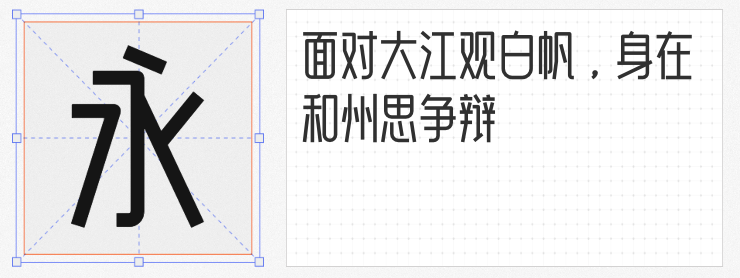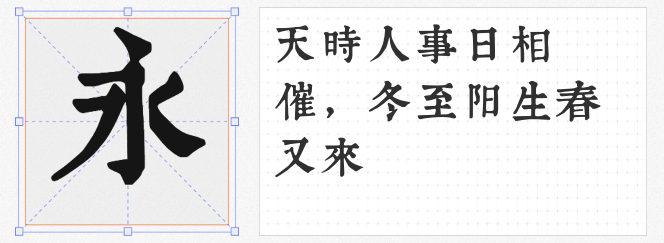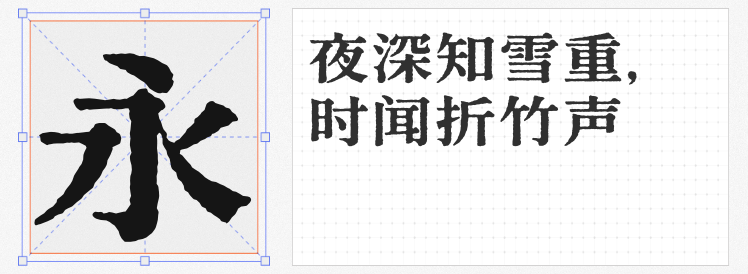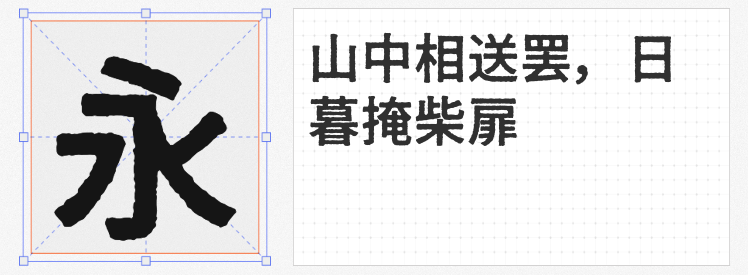
在复古风格的设计中,字体是连接过去与现在的视觉纽带。以下四款免费商用字体,以独特的造型语言与岁月质感,为设计注入跨越时空的叙事感。
1. 白无常可可体 Medium
这款修长挺拔的创意字体,以干净的几何线条重构汉字结构。转角处采用规则的圆形切割,在硬朗的直线中融入圆润的呼吸感,形成理性与感性的微妙平衡。其简洁的笔画与克制的装饰性,既保留了工业时代的机械美学,又通过修长比例暗合复古海报的优雅气质。适用于蒸汽朋克主题、科技品牌怀旧营销等场景,为现代设计注入一丝未来主义的复古情怀。
2. 寒蝉活黑体 復 Bold
基于ShipporiAntique改造的这款黑体,完美复刻了老式印刷品的磨损质感。斑驳的笔画边缘仿佛被岁月侵蚀,粗犷的笔触中透露出手工印刷的温度。作为思源黑体的衍生字体,它在保留现代黑体易读性的同时,通过纹理处理赋予文字历史厚重感。特别适合复古电影海报、旧时光主题包装设计,或需要营造沧桑感的品牌故事呈现。
3. 润植家康熙字典美化体 正常
这款以康熙字典为蓝本的宋体,通过不均匀的字体大小与斑驳的墨色,还原了古籍印刷的天然美感。横细竖粗的经典结构中,刻意保留的笔画瑕疵与墨色晕染,让每个字符都成为承载时间的容器。在传统茶饮包装、国风文创产品、古籍数字化设计等领域,这款字体能瞬间唤醒东方美学基因,构建跨越时空的文化对话。
4. 寒蝉活宋体 復 ExBold
源自ShipporiMincho的改造字体,将思源宋体的优雅与做旧工艺完美融合。ExBold的粗壮笔画强化了视觉冲击力,而斑驳的纹理处理则赋予文字手写原稿的质朴感。其独特的日式复古气质,既适合昭和风广告设计、老字号品牌重塑,也能为现代设计增添一份克制而含蓄的年代感,在秩序与破败的对比中展现时间的美学张力。
这四款字体如同四把时光钥匙,让设计师得以在数字时代自由穿梭于不同的历史维度。它们的免费商用属性,更让复古美学的表达不再受限于成本,为创意工作者提供了触手可及的时间素材库。